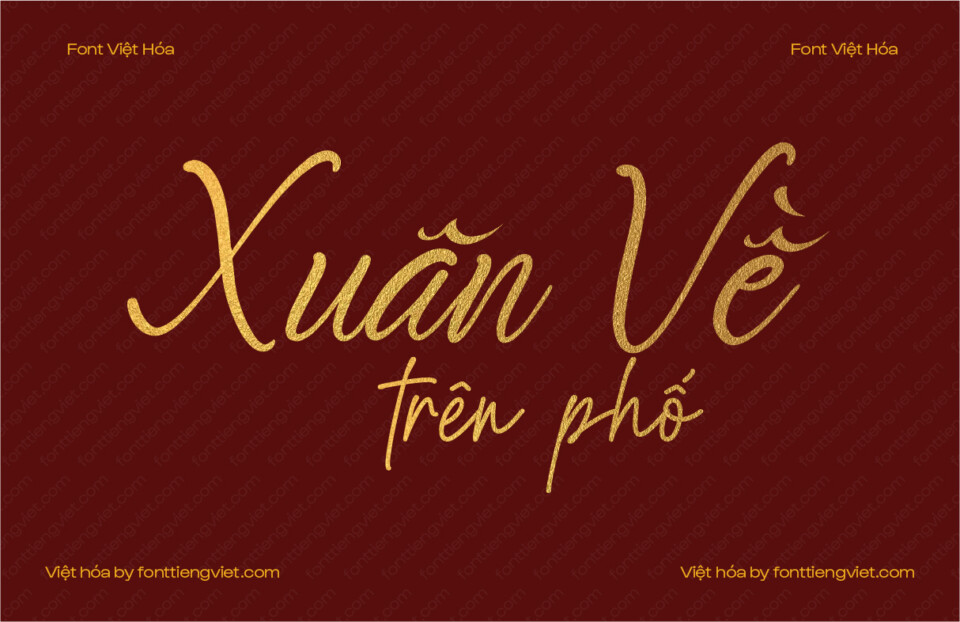
Font Việt hóa 1FTV VIP Martinez Gauttaro – Font Việt hóa tết – Sự lựa chọn hoàn hảo cho thiết kế chào xuân
Giới thiệu về Font Việt hóa 1FTV VIP Martinez Gauttaro – Font Việt hóa tết
Trong không khí rộn ràng của những ngày cuối năm, việc tìm kiếm một bộ Font Chữ phù hợp để truyền tải thông điệp may mắn là vô cùng quan trọng. Font Việt hóa 1FTV VIP Martinez Gauttaro – Font Việt hóa tết là sự kết hợp tinh tế giữa nét chữ hiện đại và phong cách nghệ thuật độc đáo. Với các đường nét thanh thoát nhưng không kém phần mạnh mẽ, bộ font này mang đến hơi thở mới lạ cho các ấn phẩm truyền thông, giúp người thiết kế dễ dàng tạo nên những tác phẩm ấn tượng cho mùa lễ hội truyền thống lớn nhất trong năm tại Việt Nam.
Đặc điểm nổi bật của Font Việt hóa 1FTV VIP Martinez Gauttaro
Bộ font này được tối ưu hóa hoàn toàn cho bảng mã tiếng Việt, giúp người dùng không còn lo lắng về lỗi hiển thị dấu hay các ký tự đặc biệt. Martinez Gauttaro sở hữu cấu trúc ký tự cân đối, phù hợp cho cả tiêu đề lẫn nội dung ngắn. Đặc biệt, khi sử dụng làm Font Việt hóa tết, nó giúp các câu chúc, thiệp mời hay banner quảng cáo trở nên sang trọng và thu hút hơn. Sự linh hoạt trong phong cách cho phép bạn áp dụng font vào nhiều mục đích khác nhau từ thiết kế bìa sách, poster sự kiện cho đến trang trí bao lì xì.
Ứng dụng Font Việt hóa 1FTV VIP Martinez Gauttaro trong giáo dục và đời sống
Tại các trường học, giáo viên và học sinh có thể sử dụng bộ font này để trang trí bảng tin hoặc làm báo tường chào xuân. Việc sử dụng những phông chữ đẹp mắt không chỉ giúp không gian lớp học thêm phần sinh động mà còn khơi gợi cảm hứng sáng tạo cho các em học sinh. Đây là công cụ đắc lực để biến những ý tưởng thiết kế đơn giản trở thành những sản phẩm chuyên nghiệp, mang đậm bản sắc văn hóa dân tộc trong dịp Tết Nguyên Đán.
Tổng kết về Font Việt hóa 1FTV VIP Martinez Gauttaro – Font Việt hóa tết
Việc lựa chọn Font Việt hóa 1FTV VIP Martinez Gauttaro – Font Việt hóa tết sẽ giúp dự án của bạn đạt được sự hài hòa giữa yếu tố thẩm mỹ và nội dung. Hãy tận dụng ngay bộ Font Miễn Phí, Font Việt Hóa, Font Việt hóa 1FTV VIP Martinez Gauttaro – Font Việt hóa tết này để làm mới các thiết kế của mình, tạo nên những món quà tinh thần ý nghĩa dành tặng người thân và bạn bè trong mùa xuân mới.